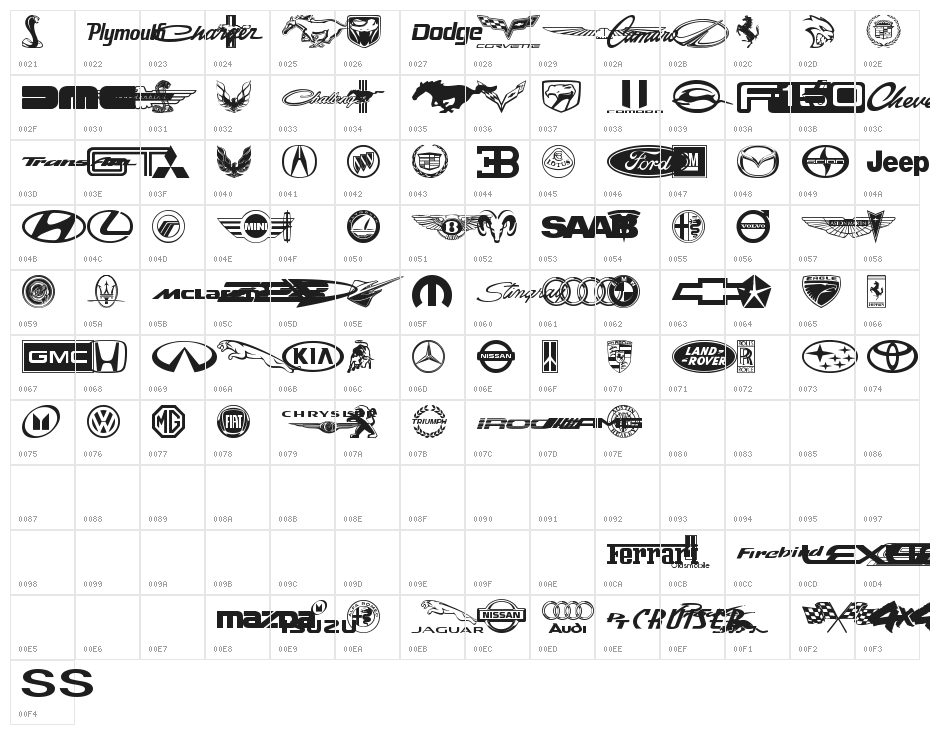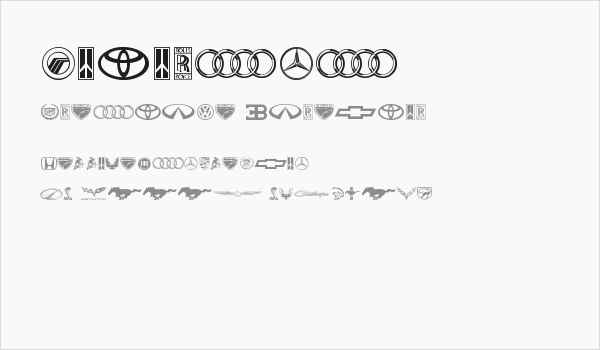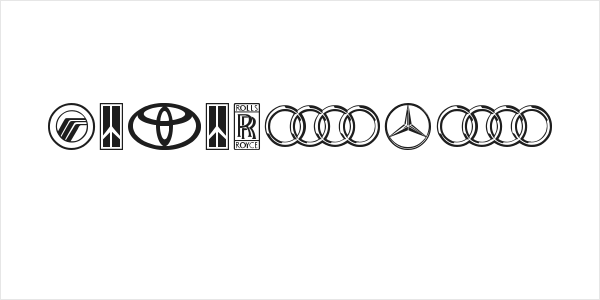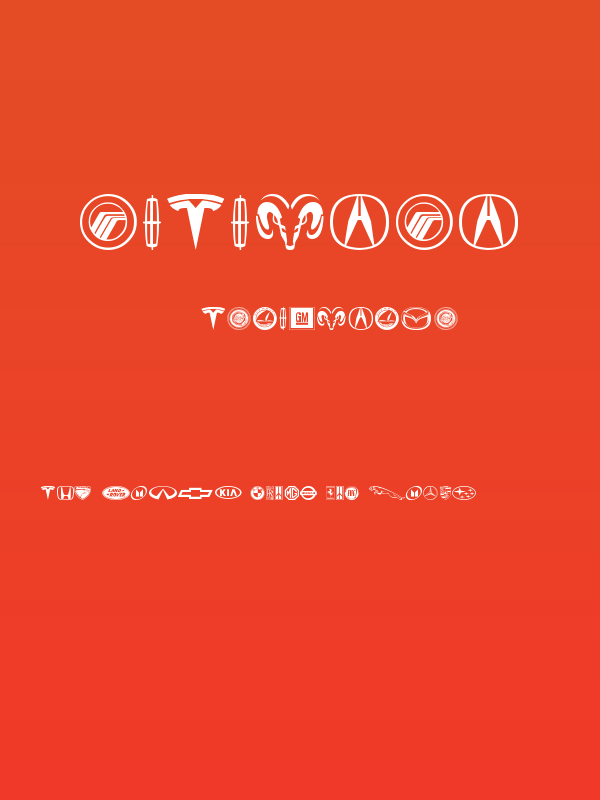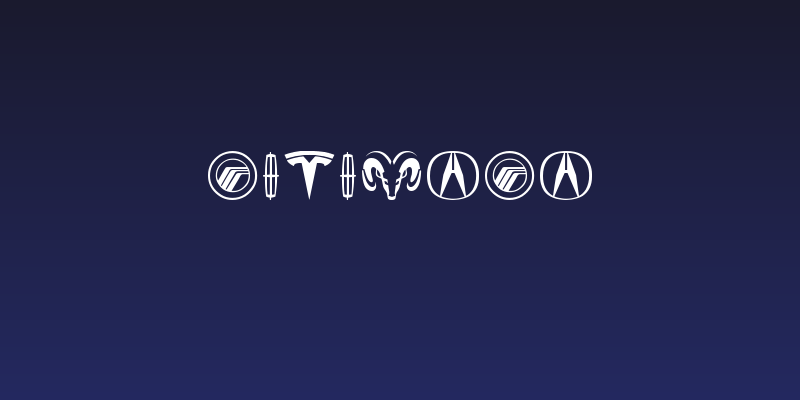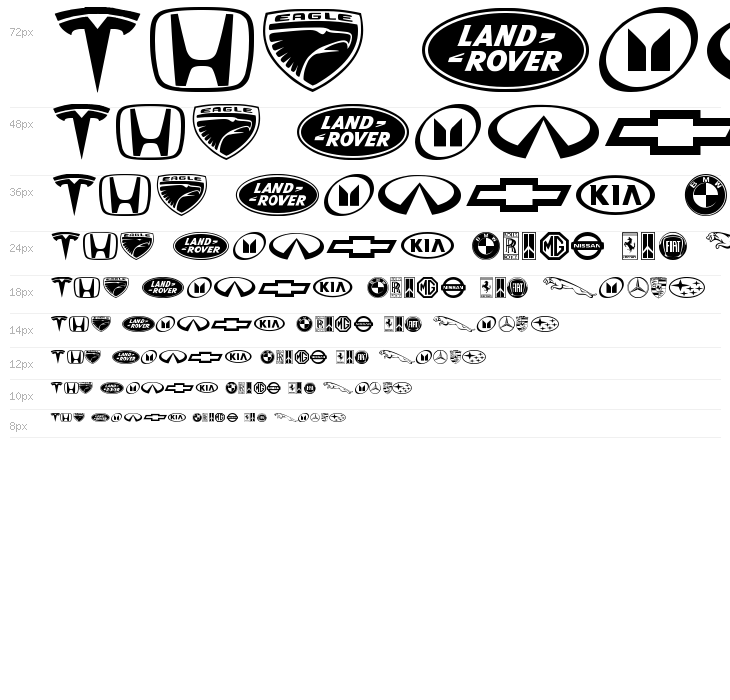
Motorama Font
| Stile generale | Mixed (Modern, Classic, Decorative, Script, Emblematic) |
| Caso d'uso | Branding, Logos, Posters, Signage |
| Progetti proposti | Automotive branding, car enthusiast posters, dealership signage, automotive history presentations, logo design inspiration. |